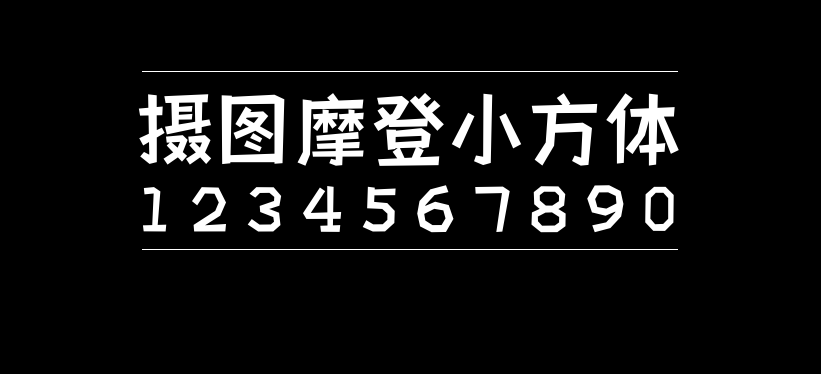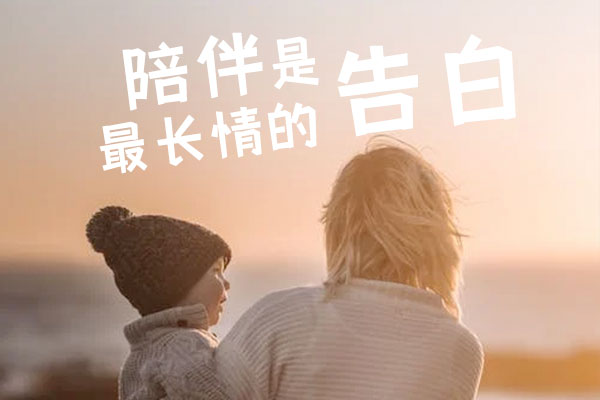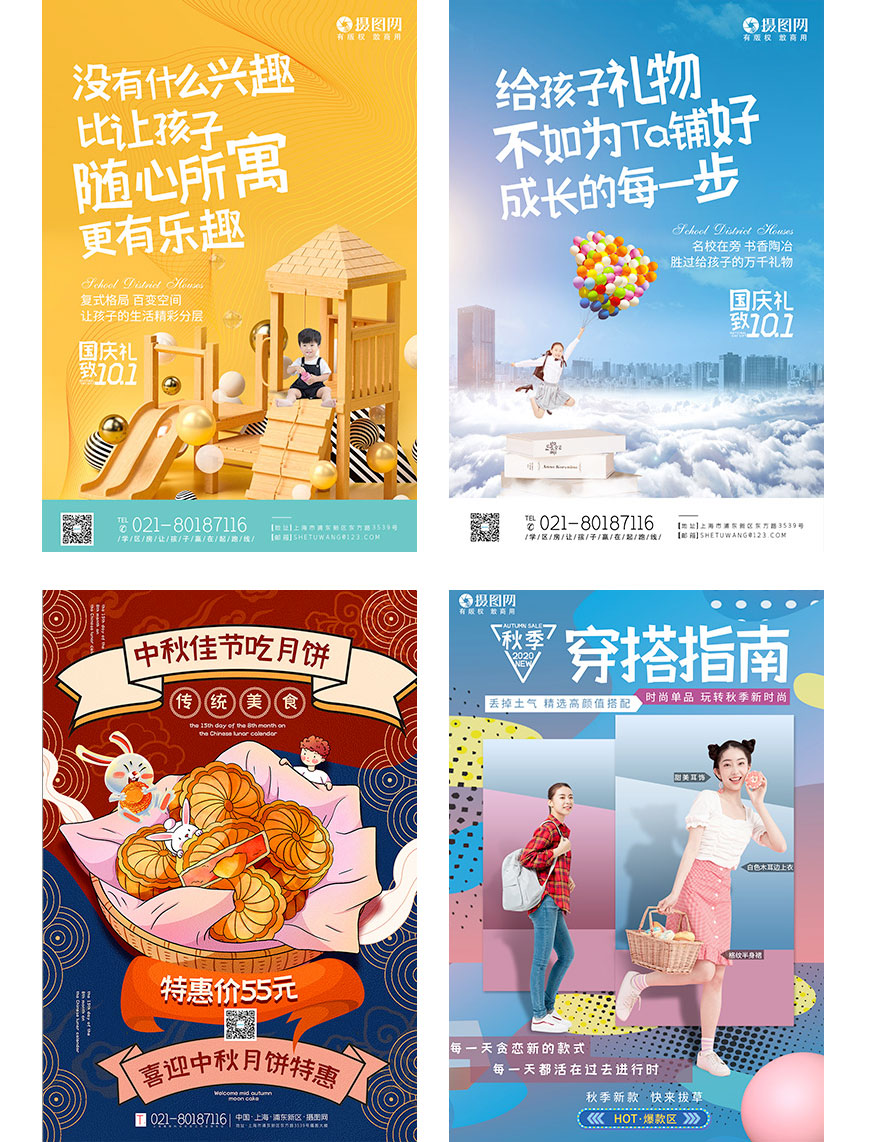
摄图摩登小方体
摄图摩登小方体是摄图网(699pic.com)联合iFonts共同推出的一款公益创意黑体字,由摄图网委托iFonts制作,版权归摄图网所有,本字库供社会各界全渠道商用。
字体的设计灵感来自对未来空间的想象,传达给人一种未来与现实的交际感。笔画方正质朴而又不失灵气活力,适中的字体笔画粗度和几何感的细节设计,让字体有良好的视觉应用表现。通过对字体负形空间的处理,使字体整体感觉稳重端正而又不呆板,更加具有趣味性。适合电商、广告、美食等商业宣传和包装设计,以及社交网络的个性化用字。